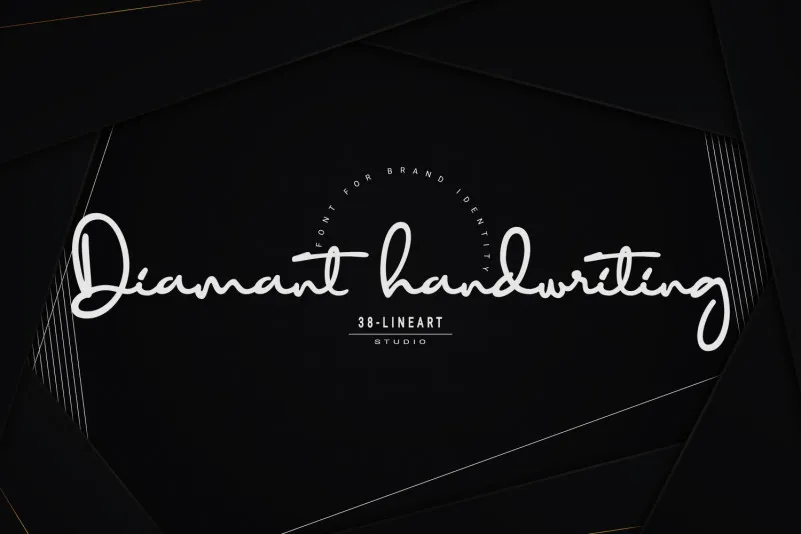
Diamant handwriting Font – Download Grátis
A Diamant Font é uma tipografia para escrita livreto vertical que retrata a estética elegante de um traço fino. Este estilo se destaca por sua forma ondulada horizontal, que simboliza serenidade na escrita. Cada sílaba da fonte foi programada com um ritmo específico, o que resulta em combinações suaves entre letras altas e baixas. Experimente-a, e verá como a Diamant Font cria uma atmosfera de calma em qualquer texto digitado. Através do OpenType, esta fonte oferece funções avançadas como ligaturas, alternâncias estilísticas e alternâncias contextual. Esta integração faz com que seu design seja automatizado, enquanto também proporciona acesso a todas as alternativas (aalt). Este recurso permite escolher o glyph personalizadamente conforme sua preferência. Essas características oferecem uma experiência de escrita fluida e precisa, proporcionando um toque elegante e moderno aos textos. Experimente a Diamant Font e veja como ela pode transformar seu design gráfico, garantindo que todas as suas criações se destaquem por sua sofisticação e cuidado com os detalhes.